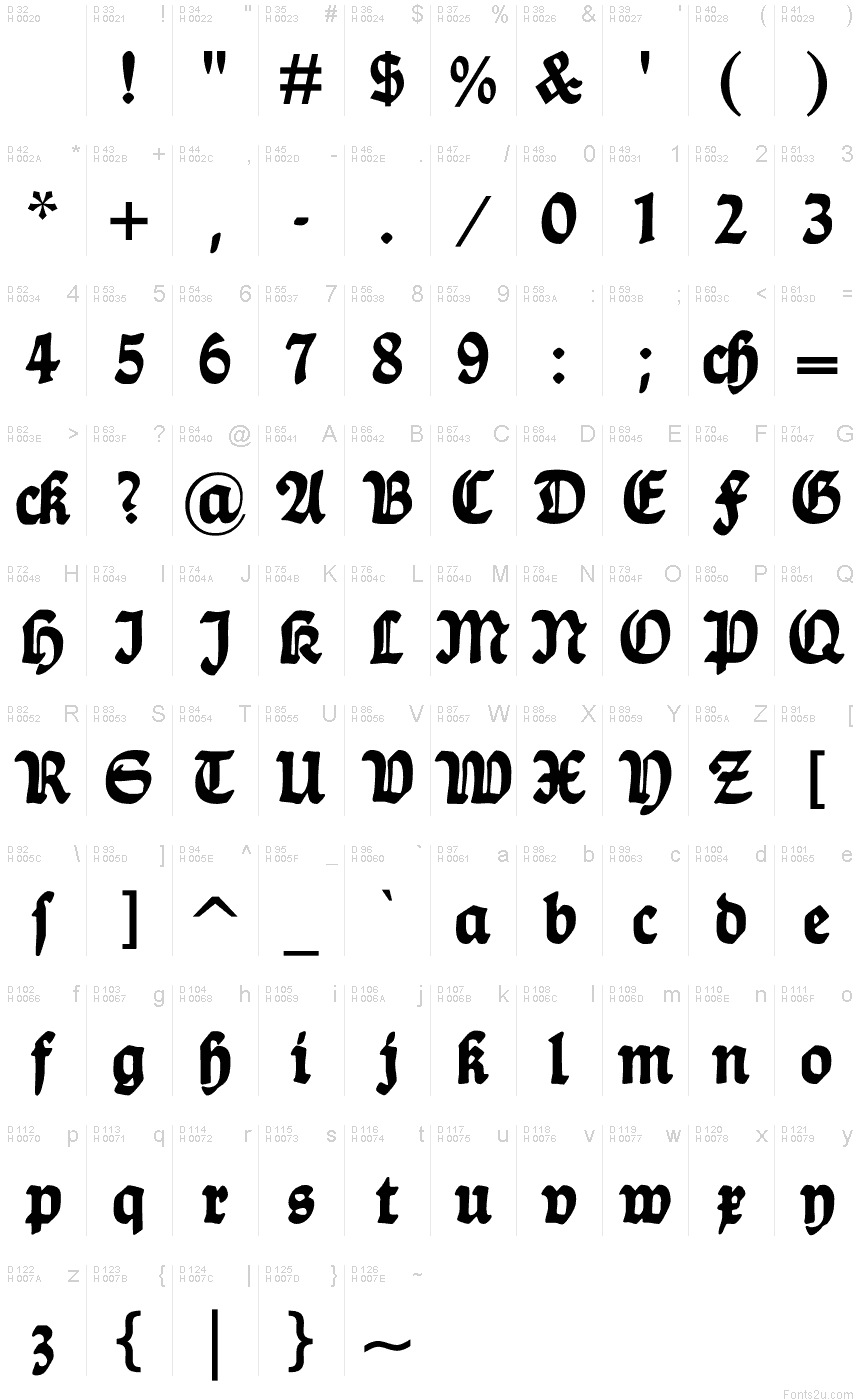
خط Ballade Bold من تصميم Dieter Steffmann (Typographer Mediengestaltung) هو خط قوطي مجاني من القرون الوسطى يتميز بضربات سميكة تشبه الحبر ومنحنيات منحوتة تبدو وكأنها مقتبسة من مخطوطة مزخرفة. يضغط وزنه العريض الأشكال الداكنة في نسيج كثيف، مما يضفي على الكلمات حضوراً مراسمياً يبدو وكأنه منحوت في الصخر. الحروف مزخرفة ولكن دون أن تضيع في الفوضى، لذا ستحصل على ذلك الطابع الدرامي القديم مع الحفاظ على وضوح العناوين وقوتها.
استخدام Ballade Bold، كجزء من عائلة Ballade، ينقل مشاريعك فوراً إلى عالم من النبالة والخيال والفلكلور؛ فهو مثالي لأغلفة الكتب، وعناوين الألعاب، وشعارات الفرق الموسيقية، وملصقات المهرجانات، وملصقات البيرة الكلاسيكية، والقوائم ذات الطابع الخاص. يتألق هذا الخط المجاني عند استخدامه بحجم كبير، مما يسمح لإيقاعه الزاوي وفراغات الحروف الضخمة بأن تتنفس حقاً. بالنسبة للنص الأساسي، قم بدمجه مع خط serif بسيط أو sans serif نظيف، واجعل تلك الأسطر الصغيرة خفائفة وواسعة لموازنة ثقله البصري.